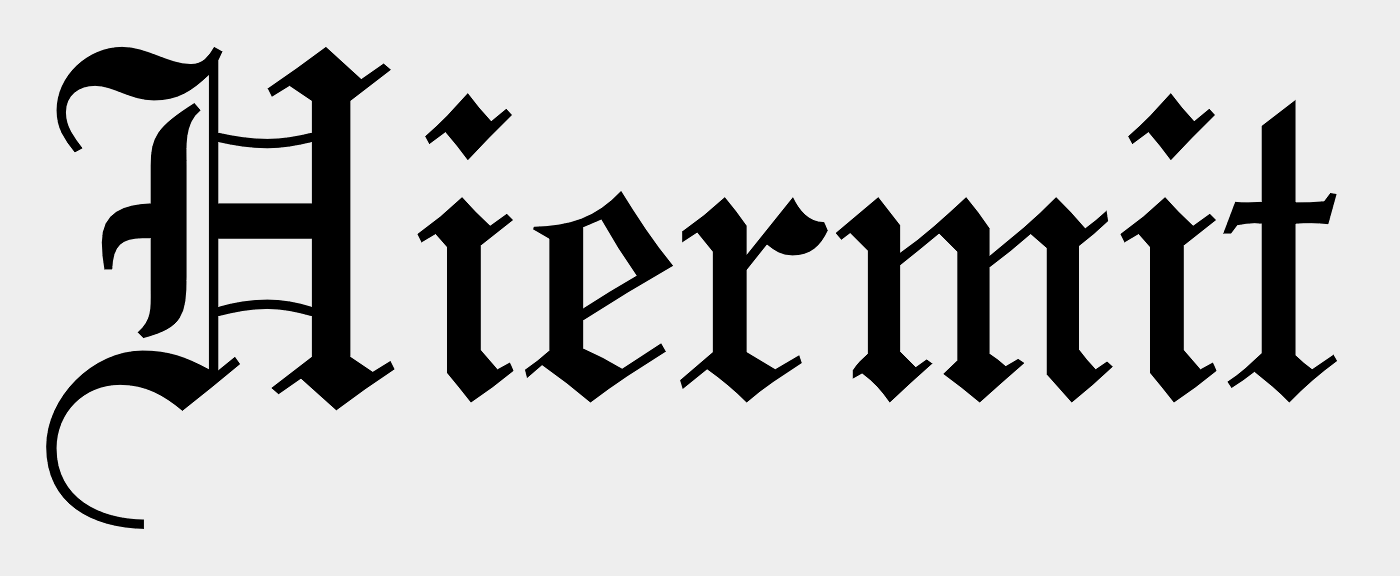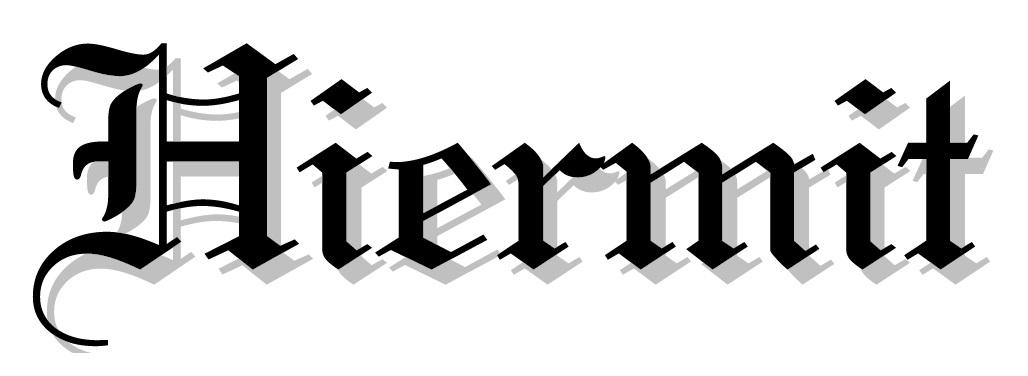
ich heiße Waldemar, ich bin neuer hier und kenne mich hier nicht aus. Ich möchte fragen welche Schrift ist das?
Das ist eine Art Old English: Myfonts bringt mit aber nur die Linotext in der gewünschten Form:
Die ist das Original zur Lincoln SM und passt auch nicht perfekt, siehe kleines t ... Mit etwas Nachdenken Fallen einem dann die vielen anderen Schriften aus der Rubrik Old English ein ... Das war was mit Ehe und Scheidung ...
Diese Schrift sollte besser passen? Fast, aber sie läuft etwas zu schmal ... Die Bitstremversionen laufen breiter.
Sollte passen ...
Breiter laufende BT-Version nachgetragen